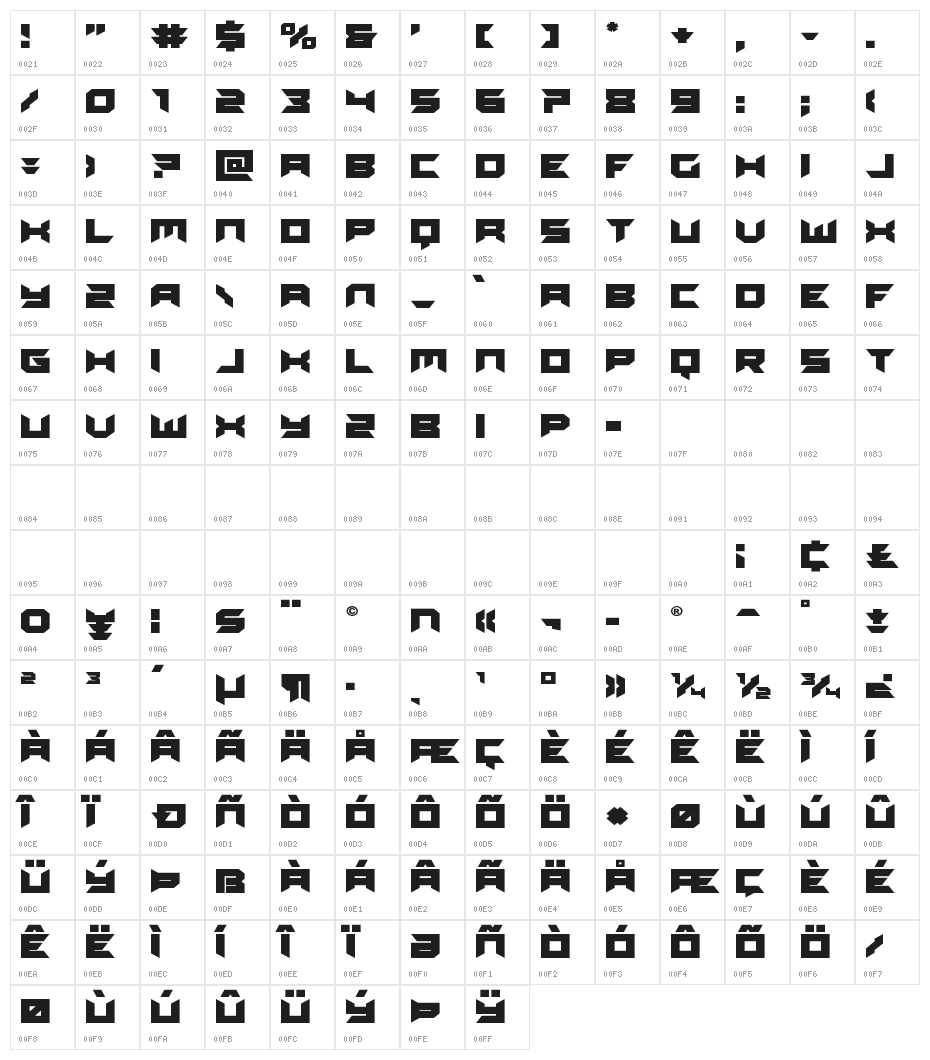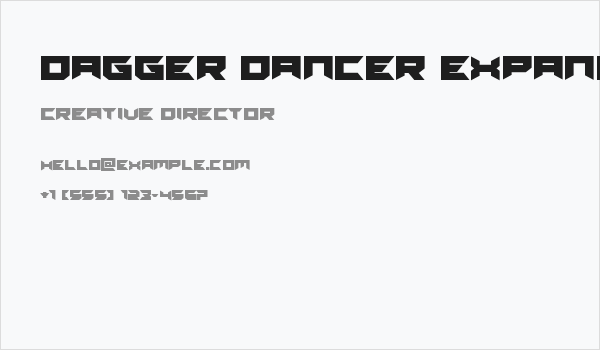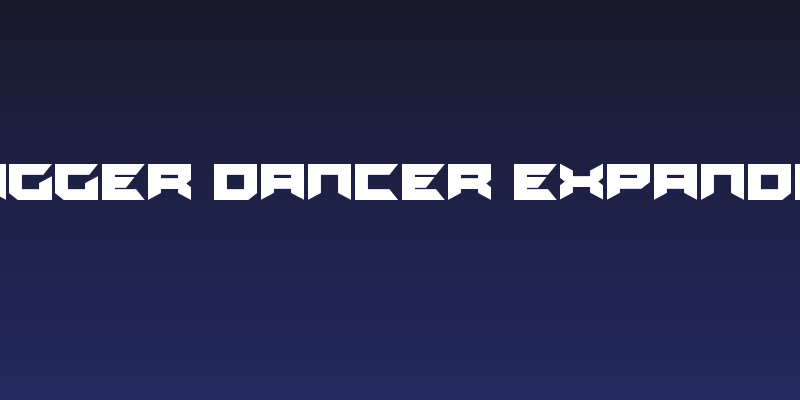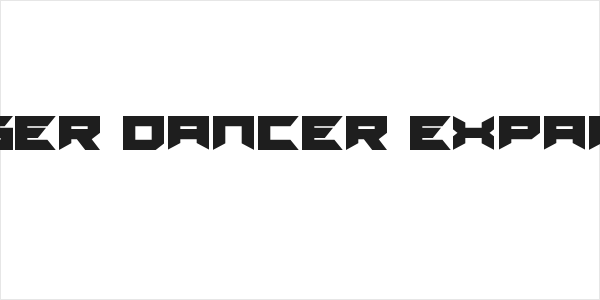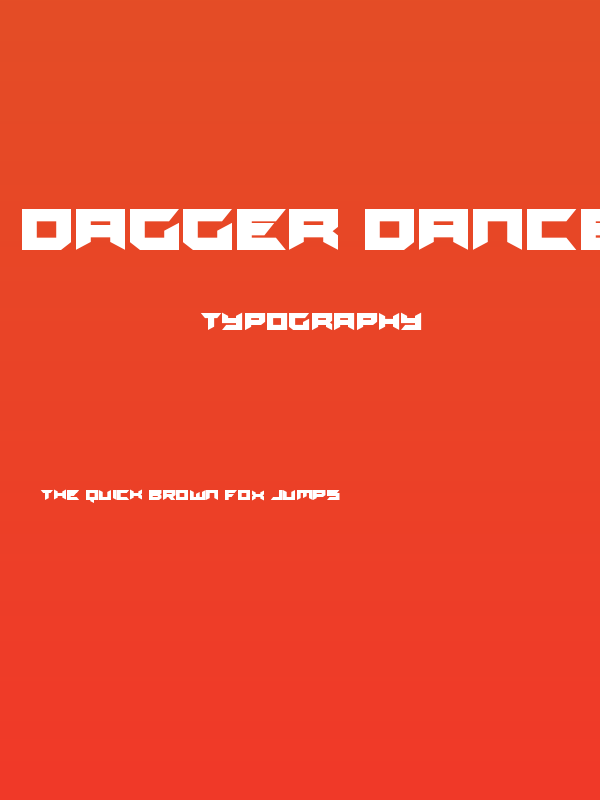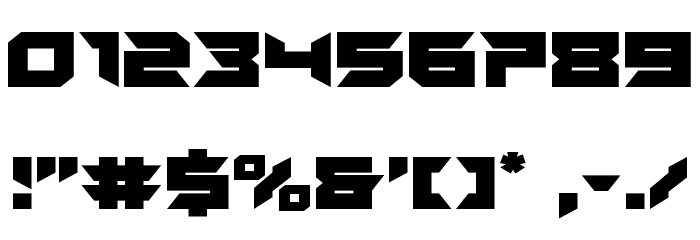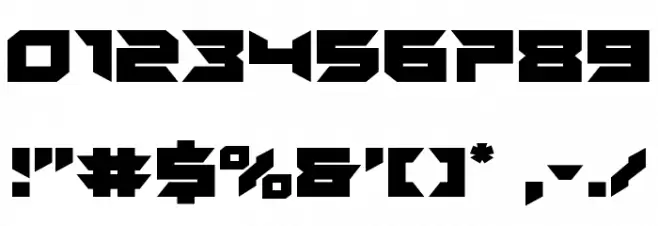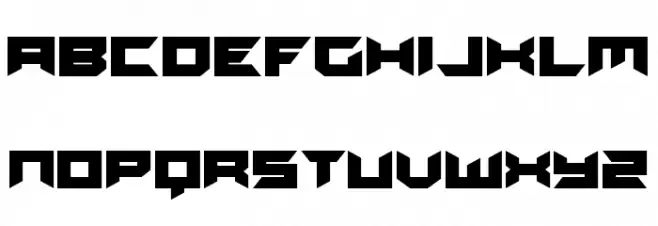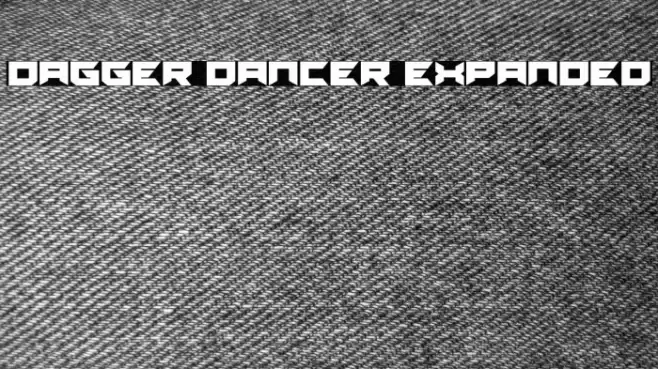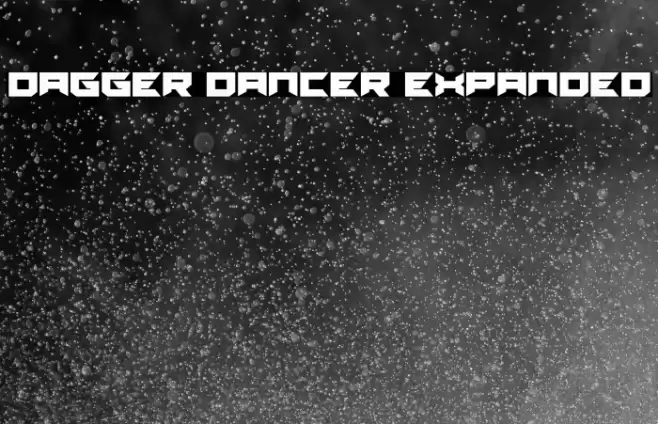
Dagger Dancer Expanded Font
✎ Futuristic
| 分类 | Futuristic |
| 宽度 | Expanded |
| 推荐项目 | Ideal for sci-fi themed designs, video game graphics, tech branding, and futuristic posters. |